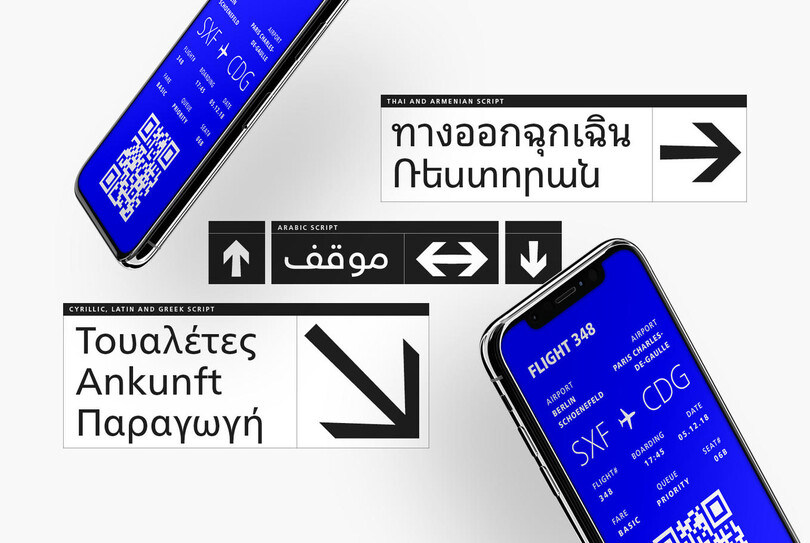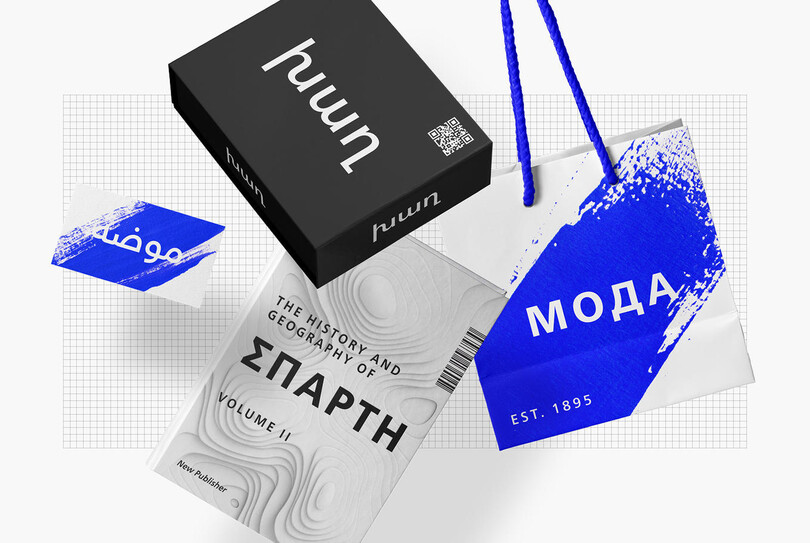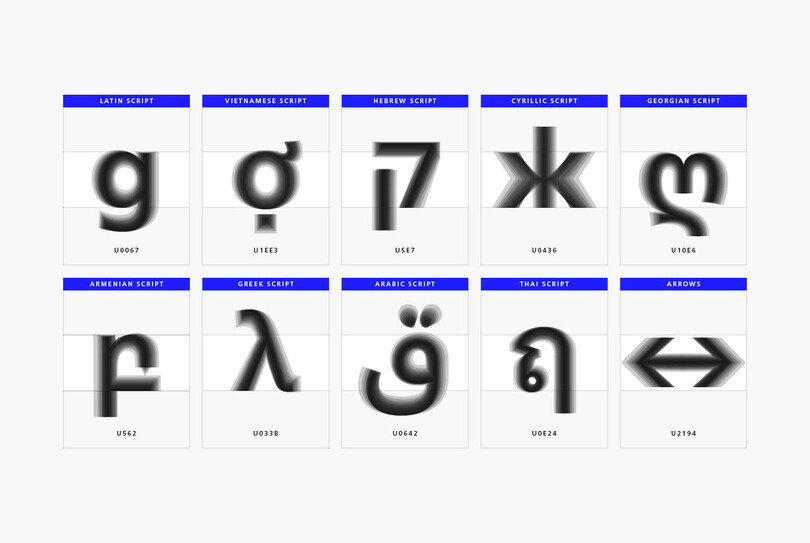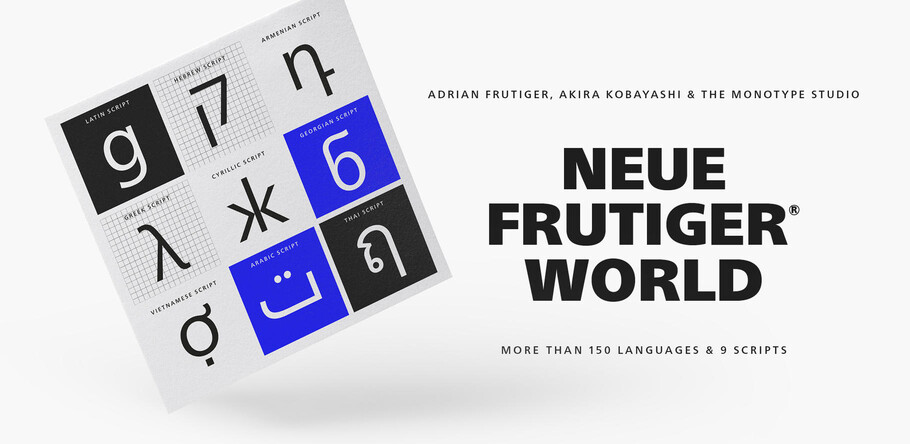
À la découverte de Neue Frutiger World.
“ Neue Frutiger World reste fidèle à l’ADN du design de l’original, mais l’élargit pour s’adapter à une multitude de langues. ”
Plus de 150 langues et systèmes de police sont pris en charge par cette superfamille internationale, qui emprunte la chaleur et la clarté du design original Frutiger et aide les marques à communiquer avec cohérence à travers le monde.
À une heure où les entreprises tendent de plus en plus à se mondialiser, les marques doivent préserver leur identité visuelle et leur ton dans toujours plus de langues et de styles de communication. Neue Frutiger World, fruit de plusieurs années de travail effectué par une équipe de typographes, répond à ce besoin grandissant.
La police originale, dont Neue Frutiger World est une extension, a été développée par Adrian Frutiger, au milieu des années 70, pour l’aéroport Paris-Charles-De-Gaulle. Son caractère lisible et accessible, décrit comme « un timbre organique et amical » par le directeur typographe Akira Kobayashi, a été soigneusement conservé.
Neue Frutiger World peut être utilisé sur une large gamme de supports, de l’impression à la sérigraphie.
Neue Frutiger World reste donc fidèle à l’ADN du design original, mais l’étend pour s’adapter à une multitude de langues. Plus de 150 langues sont prises en charge, parmi lesquelles le grec, le géorgien, l’arménien, l’hébreu, l’arabe, le thaï, le vietnamien ainsi que toutes les langues d’écriture cyrillique.
Au-delà d’une vaste palette linguistique, notamment européenne, Neue Frutiger World a été conçue avec une attention particulière pour son interaction avec les systèmes d’écriture asiatique. Cette famille garantit une harmonie entre les langues mises côte-à-côte, ainsi que l’assurance d’une image de marque cohérente pour les entreprises qui œuvrent sur des marchés internationaux. Neue Frutiger World s’accorde parfaitement avec les nouveaux CJK-Designs de Monotype : M XiangHe Hei (chinois), Tazugane Info (japonais) et Seol Sans (coréen). Cela est déterminant car, pour de nombreuses entreprises, la commande d’une police de caractères personnalisée pour couvrir ces langues est irréalisable en termes de coût et de temps.
Avec ses 10 graisses, Neue Frutiger World offre aux marques une large palette de supports linguistiques.
« Une nouvelle typographie avec une touche d’humanisme était très demandée en Chine, au Japon et en Corée » selon Akira Kobayashi, directeur typographe chez Monotype ayant supervisé l’équipe design de la Neue Frutiger World. « Nous étions convaincus que grâce à une nouvelle approche de l’original Frutiger, nous allions parvenir à la créer. »
Neue Frutiger World propose une typographie cohérente sur tous les points de contact de la marque.
« Avant Neue Frutiger World et les polices CJK qui l’accompagnent, il n’était pas facile pour les marques occidentales de trouver des typographies en chinois, japonais ou coréen qui s’accorderaient à leur design latin » ajoute Kobayashi. « S’ils pouvaient trouver une police assez proche, il n’y avait aucune garantie que la version en gras de la famille CJK soit aussi pertinente que la version en gras de leur choix latin. Neue Frutiger World offre une meilleure solution. »